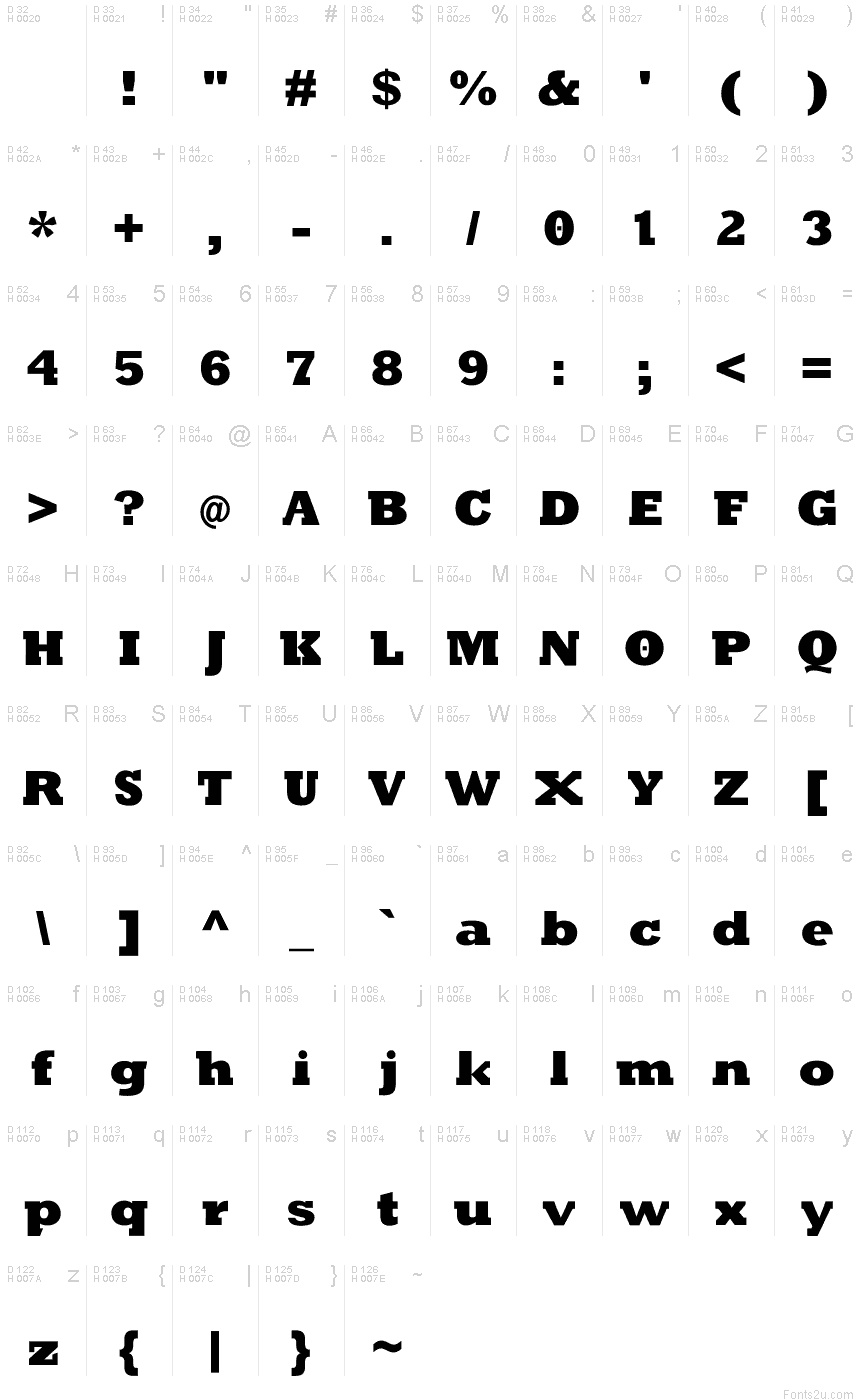
KleinSlabserifBlaxX
Klein Slabserif BlaxX od M. Kleina to bezpłatny, ultra-gruby krój typu slab serif, który uderza z siłą pieczątki. Masywne, kanciaste kształty, ostre krzywizny i charakterystyczna, jakby rzeźbiona litera „K” nadają mu wyrazisty, plakatowy klimat – jakby każda litera została wycięta w grubym drewnie i odciśnięta na papierze. Zwarty rytm oraz płaskie, ciężkie szeryfy tworzą solidną, niemal architektoniczną formę, która natychmiast przyciąga wzrok.
Używając Klein Slabserif BlaxX, nadasz nagłówkom, plakatom protestacyjnym, okładkom albumów, opakowaniom, logotypom i zinom odważny, bezpośredni charakter, który wciąż zachowuje ręczny sznyt. Ten darmowy font świetnie wygląda w dużym rozmiarze z luźniejszym światłem między literami, co pozwala masywnym kształtom odetchnąć. W tekście głównym lub drobnych detalach warto zestawić go z czystym krojem bezszeryfowym, aby zachować czytelność, podczas gdy Klein Slabserif BlaxX zadba o wizualne uderzenie.